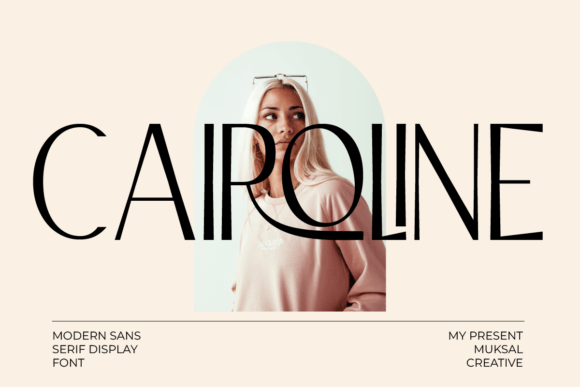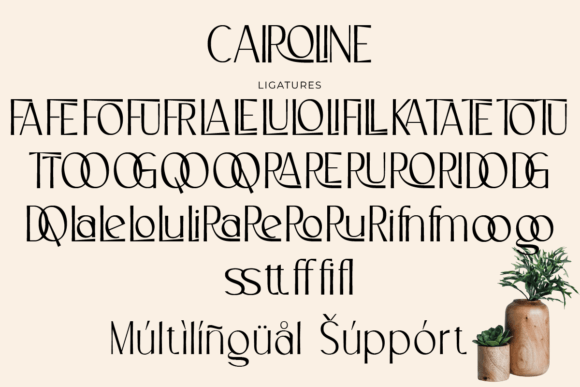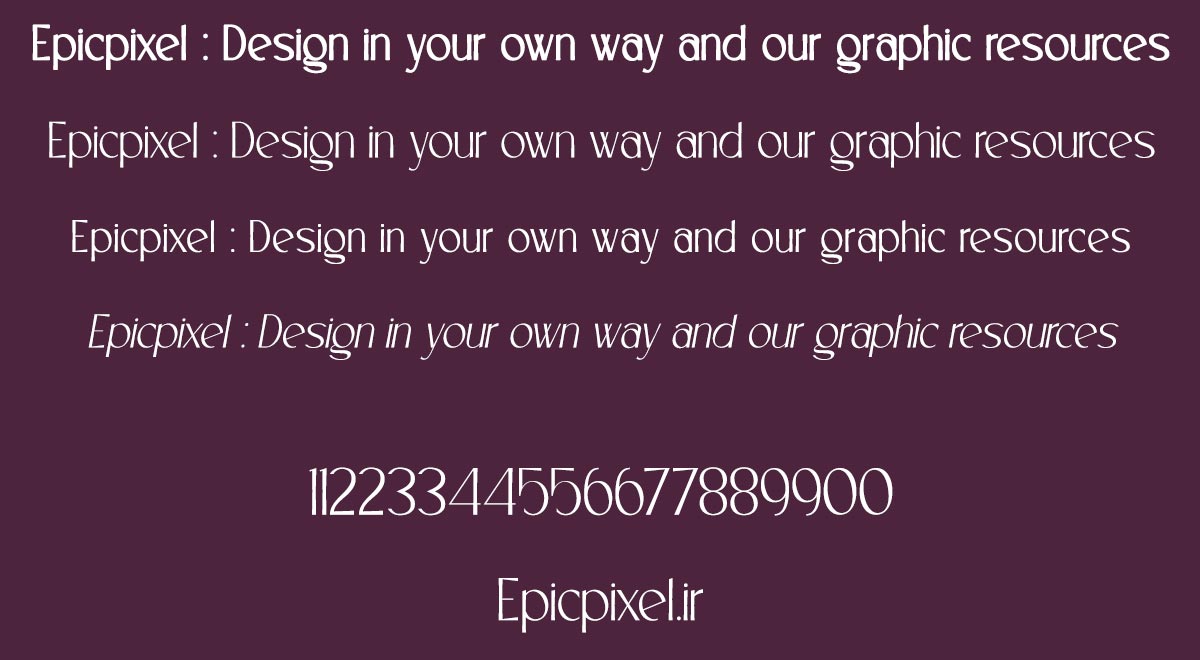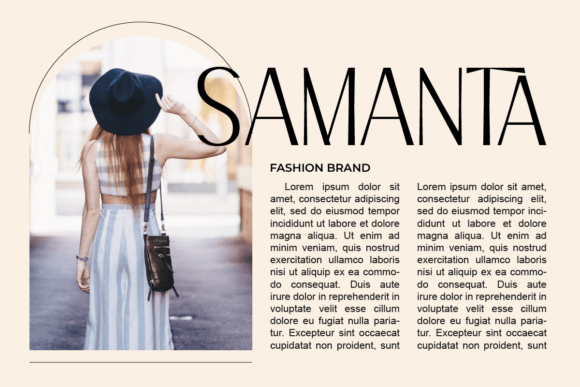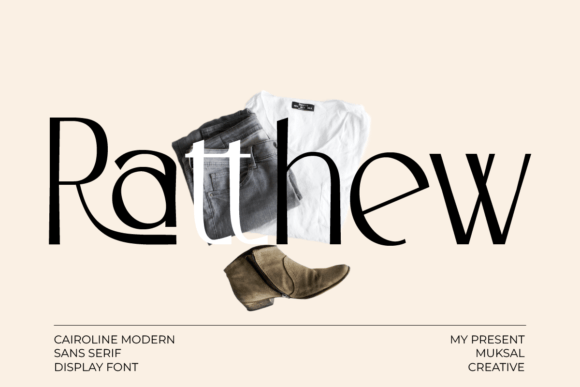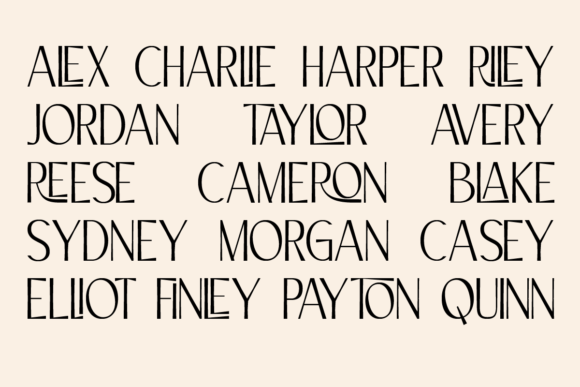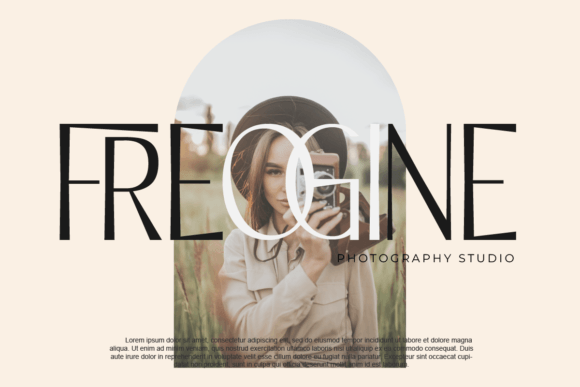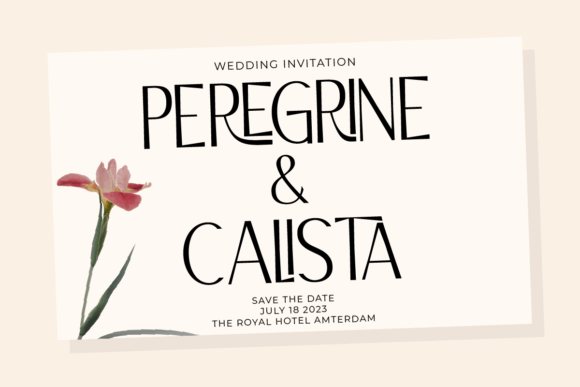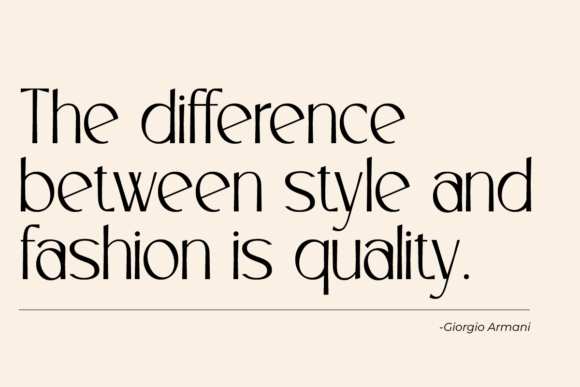
فونت Cairoline انگلیسی
فونت Cairoline انگلیسی، با طراحی مدرن و خوانایی بالای خود، گزینه ای ایده آل برای طیف وسیعی از کاربردهاست. این فونت، با ساختار هندسی دقیق و خطوط نرم، ظاهری شیک و حرفه ای به متون شما می بخشد. Cairoline در عین حال که در اندازه های بزرگ، جلوه ای چشم نواز دارد، در اندازه های کوچک نیز خوانایی خود را حفظ می کند و این ویژگی، آن را برای استفاده در وب سایت ها، اپلیکیشن ها و حتی متون چاپی با حجم بالا، مناسب می سازد.
یکی از ویژگی های برجسته Cairoline، تنوع وزن های آن است. از وزن بسیار نازک (Thin) برای طراحی های ظریف گرفته تا وزن ضخیم (Black) برای تاکید و جلب توجه، این فونت انعطاف پذیری بالایی را در اختیار طراحان قرار می دهد. این تنوع، امکان ایجاد سلسله مراتب بصری قوی و جذاب را در طراحی ها فراهم می کند. با این حال، این تنوع زیاد ممکن است در پروژه هایی که نیاز به سرعت عمل بالا دارند، کمی زمان بر باشد، زیرا انتخاب وزن مناسب نیازمند بررسی دقیق است.
فونت Cairoline با پشتیبانی از طیف گسترده ای از حروف و علائم، از جمله حروف لاتین، اعداد و نشانه های نگارشی، نیازهای مختلف کاربران را پوشش می دهد. این فونت، با وجود ظاهر مدرن خود، حس گرما و صمیمیت را نیز منتقل می کند و این ویژگی، آن را برای استفاده در برندینگ و تبلیغات نیز مناسب می سازد. البته، باید توجه داشت که Cairoline ممکن است برای متونی با حال و هوای سنتی یا کلاسیک، انتخاب مناسبی نباشد. در مجموع، Cairoline با ترکیبی از زیبایی، خوانایی و کارایی، انتخابی هوشمندانه برای طراحان و کاربران حرفه ای است.
| ⭐ توضیحات | Caroline Modern Display sans serif فونت، حروف ویژه، تزئینات و پشتیبانی چند زبانه. این یک فونت بسیار متنوع است که در اندازه های بزرگ و کوچک عالی کار می کند. ایده آل برای پروژه های تحریریه، طراحی لوگو، برند لباس، بسته بندی محصول، سرصفحه مجلات، یا به سادگی به عنوان یک پوشش متنی شیک برای هر تصویر پس زمینه.فونت پیشگان فارسیدانلودفرمت فایل: امکانات: |